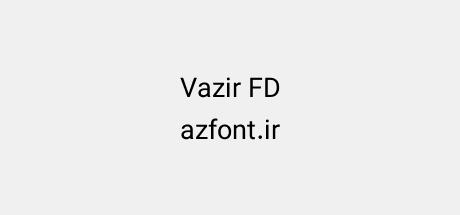
Vazir FD
فونت زیبای رایگان Vazir FD
قلم زیبای Vazir FD از سری قلم های بسیار زیبا برای تایپوگرافی و لوگو تایپ می باشد.این قلم در وزن FD و توسط Saber Rastikerdar طراحی و منتشر شده است.
DejaVu fonts team - Redesigned by Saber Rastikerdar